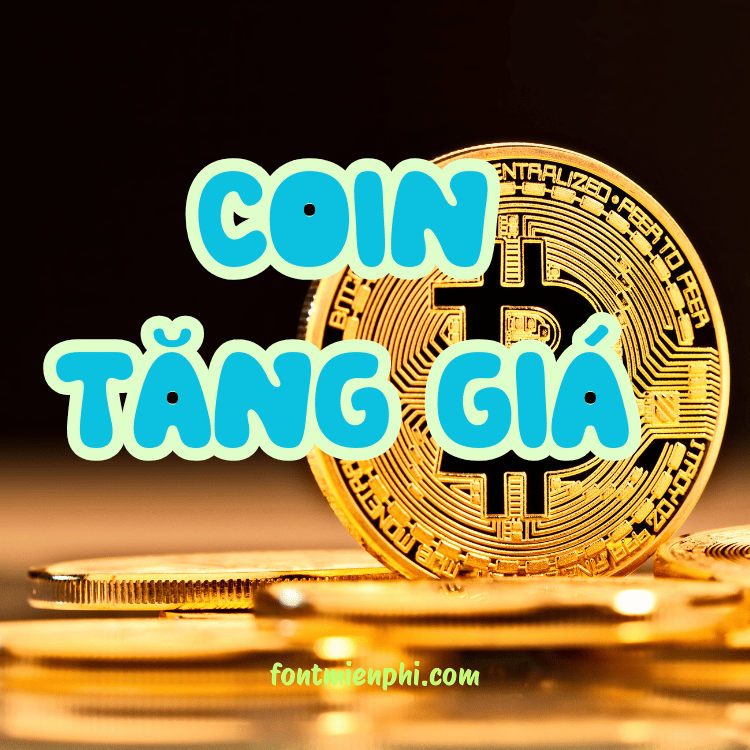
Font Việt hóa FMP Lucky vip
Font Việt Hóa FMP Lucky VIP – Nét Chữ Độc Đáo, Sang Trọng
Font Việt hóa FMP Lucky VIP là bộ font chữ nghệ thuật được thiết kế tỉ mỉ, phù hợp cho các dự án sáng tạo, thiết kế đồ họa, in ấn và quảng cáo. Với kiểu chữ thanh lịch, đường nét mềm mại, FMP Lucky VIP mang đến phong cách sang trọng, hiện đại, giúp sản phẩm thiết kế của bạn trở nên nổi bật và ấn tượng hơn.
Đặc điểm nổi bật của FMP Lucky VIP
• Hỗ trợ tiếng Việt đầy đủ: Font được Việt hóa chuẩn, đảm bảo hiển thị rõ ràng, mượt mà với các ký tự có dấu.
• Đa dạng kiểu chữ: Phong cách chữ độc đáo, phù hợp với nhiều mục đích như logo, banner, card visit, poster…
• Chất lượng sắc nét: Font được tối ưu hóa, in ấn sắc nét ở mọi kích thước.
Font Việt hóa FMP Lucky vip